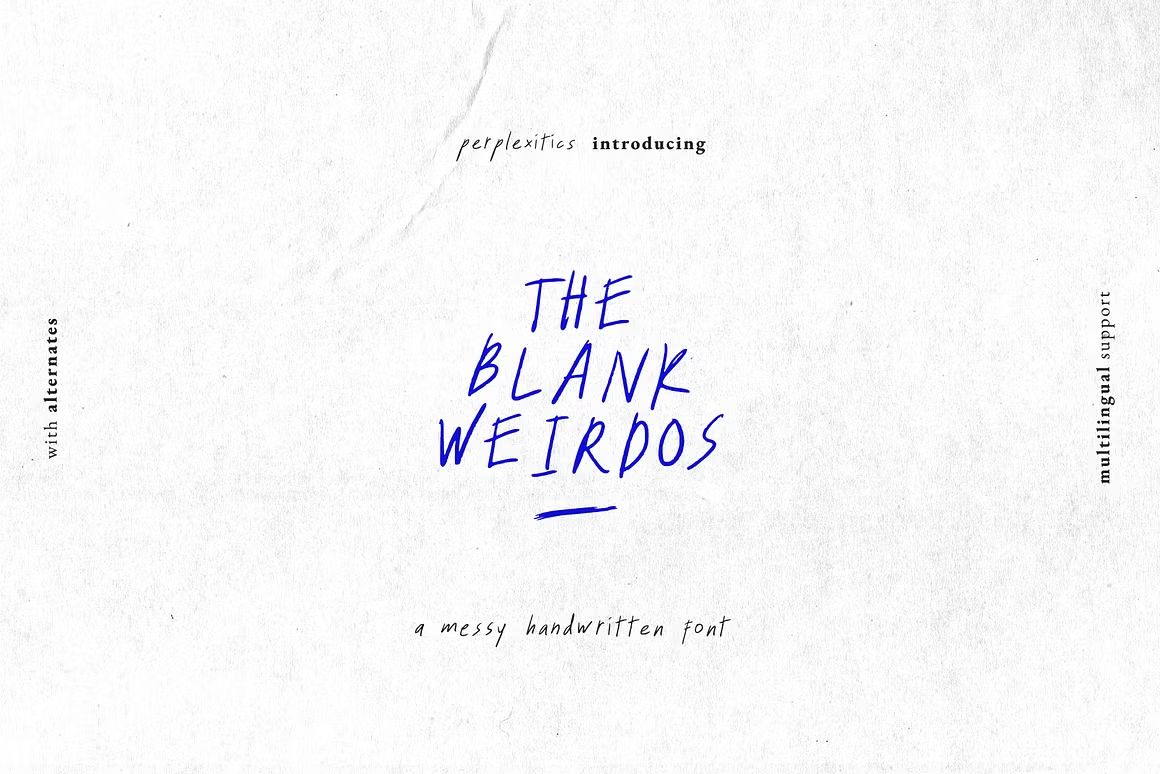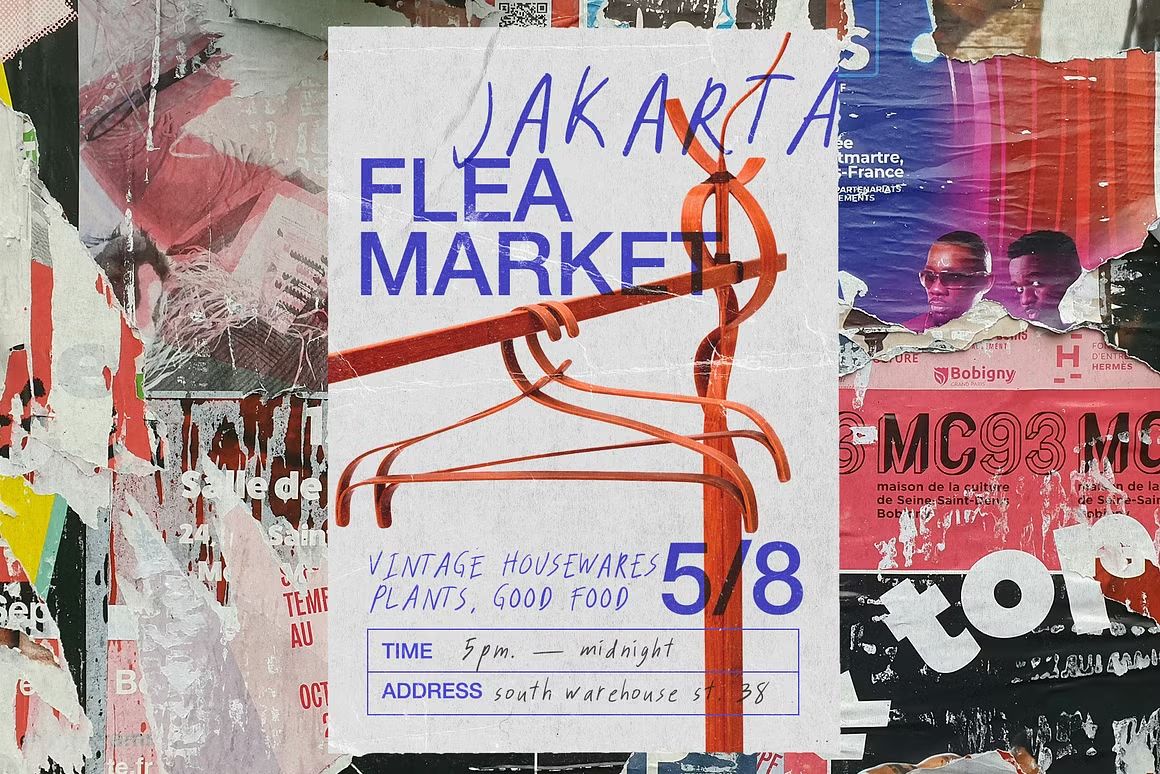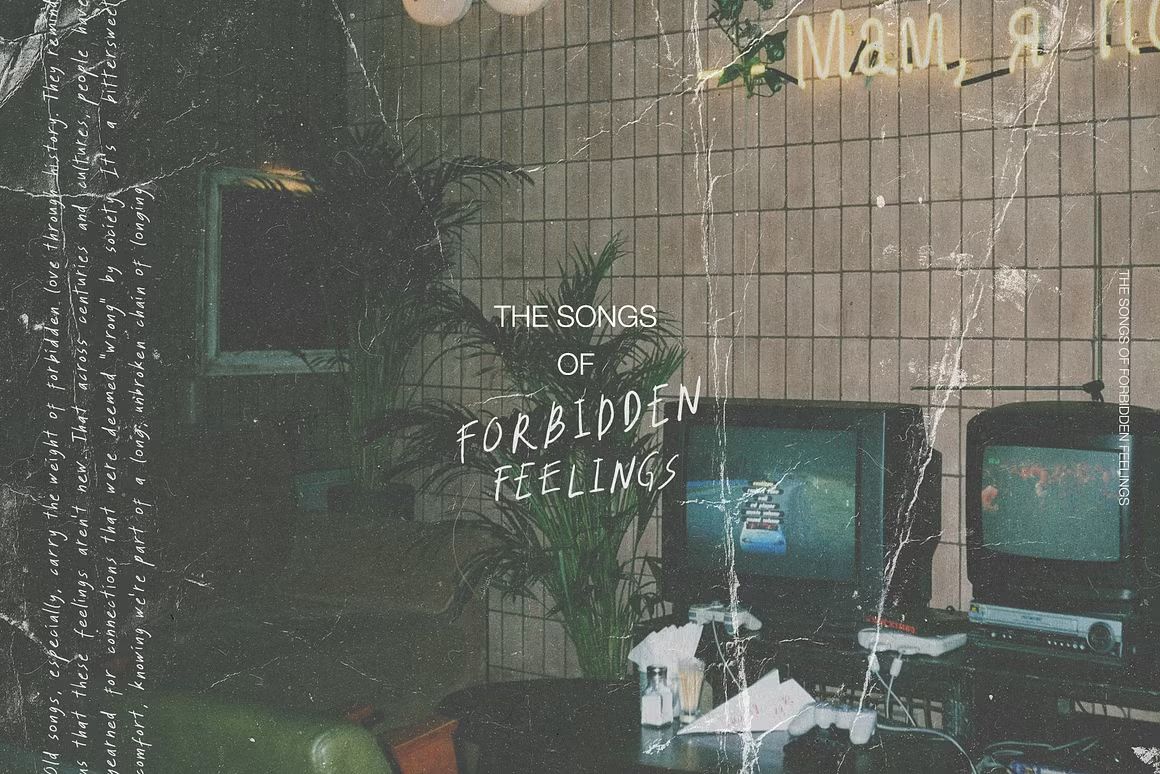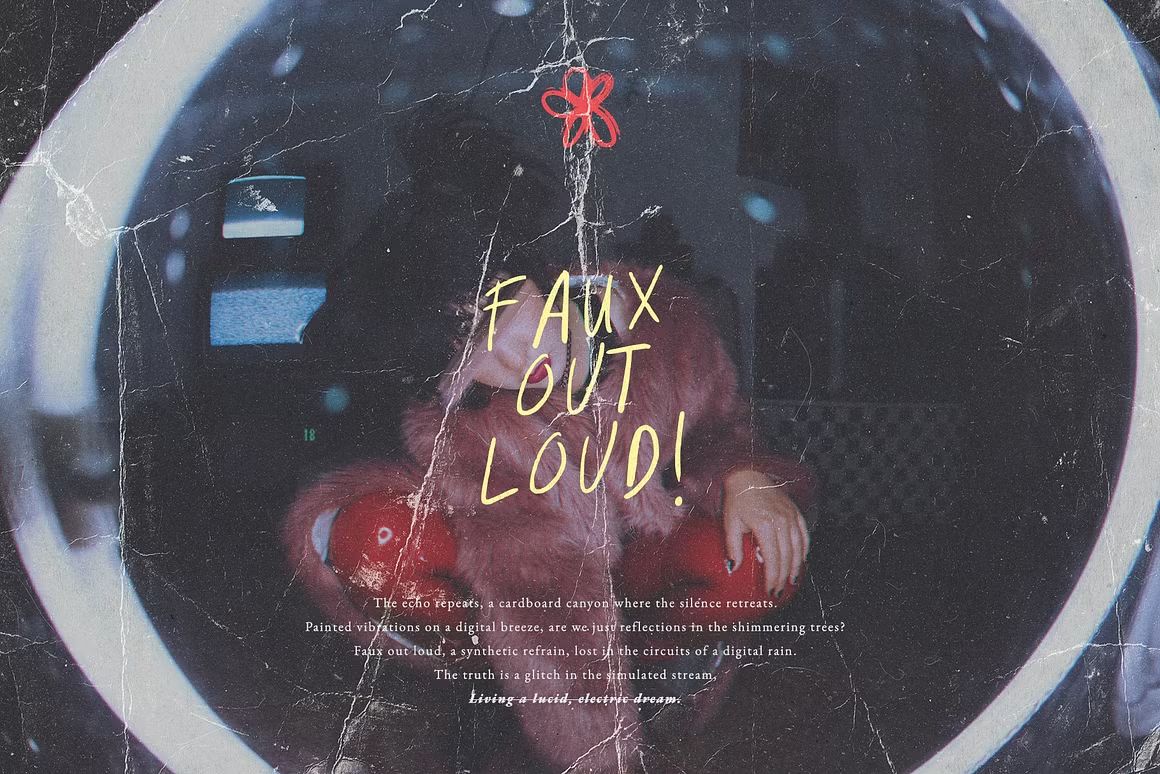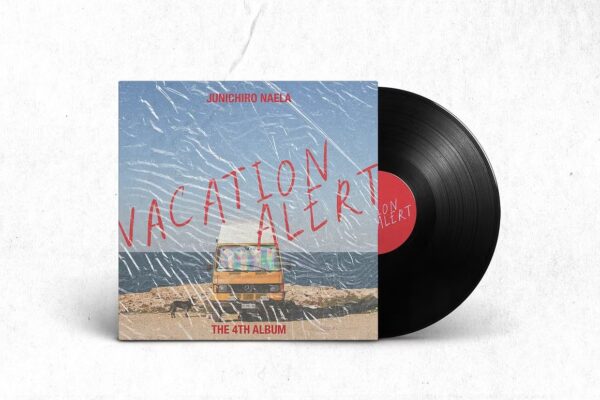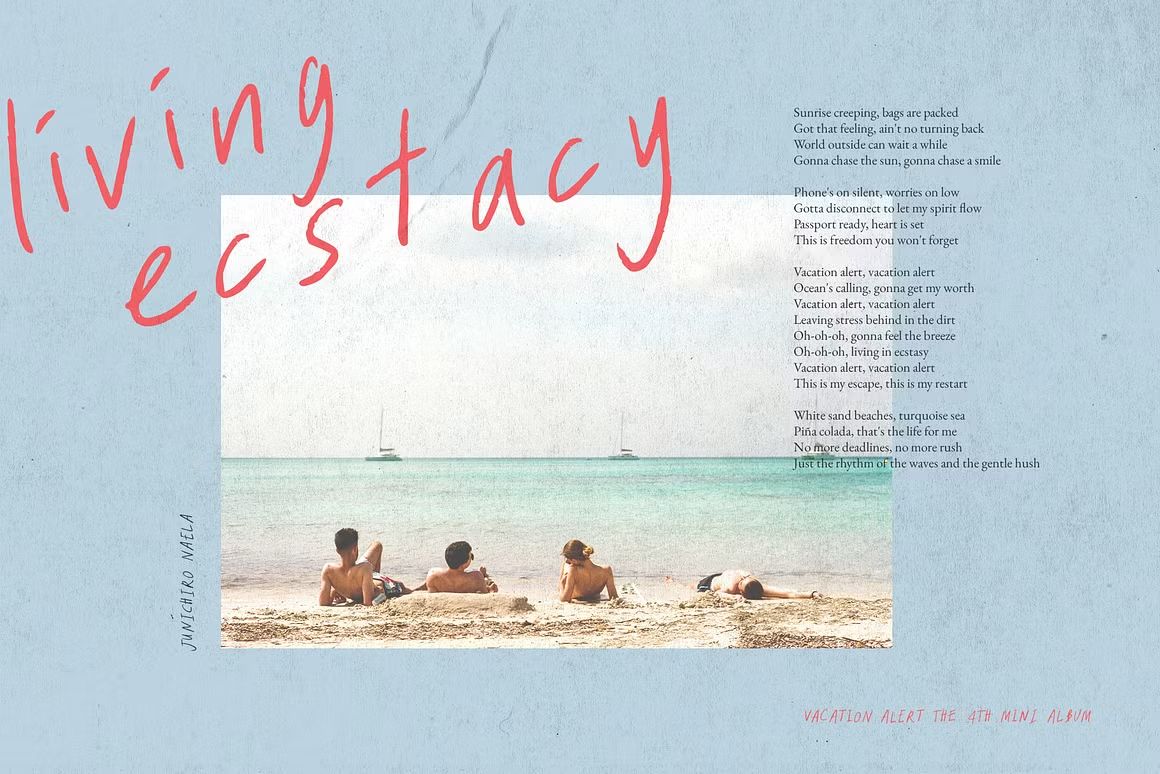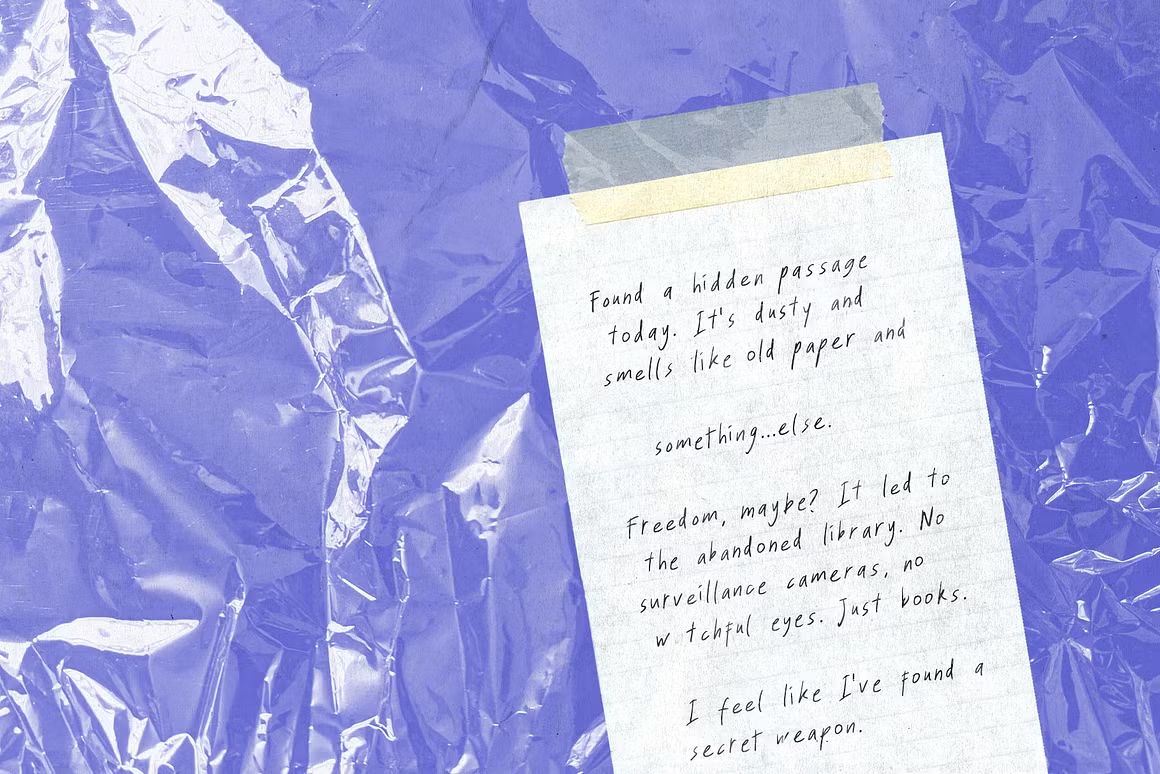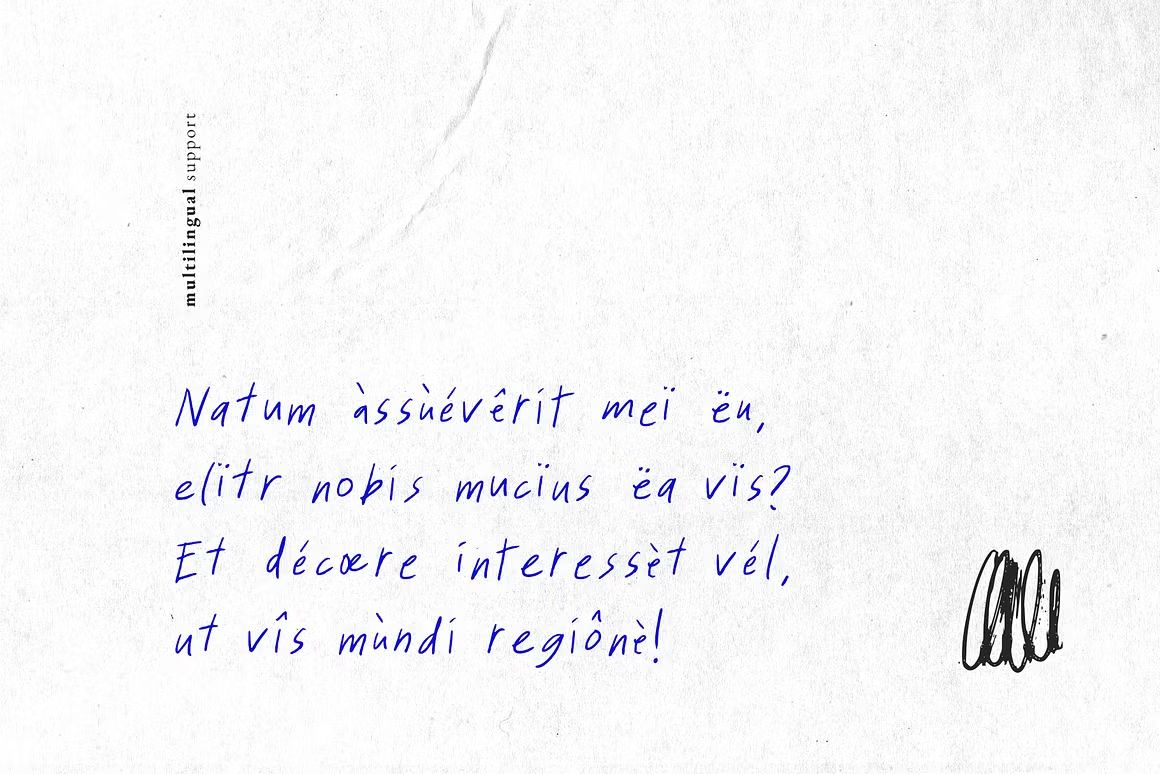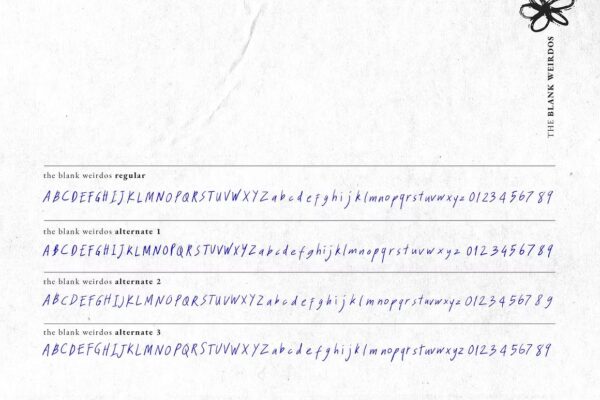
The Blank Weirdos – Handwritten Font
The Blank Weirdos adalah font handwritten bergaya unik, ekspresif, dan playful. Dengan bentuk huruf yang tidak beraturan namun tetap terbaca jelas, font ini cocok untuk desain kreatif seperti poster indie, sampul album, ilustrasi, konten media sosial, dan proyek eksperimental lainnya. The Blank Weirdos memberikan kesan spontan, artistik, dan penuh kepribadian.
• Handwritten font dengan gaya quirky dan ekspresif
• Cocok untuk desain alternatif, poster, dan konten kreatif
• Termasuk huruf besar, kecil, angka, simbol, dan karakter unik